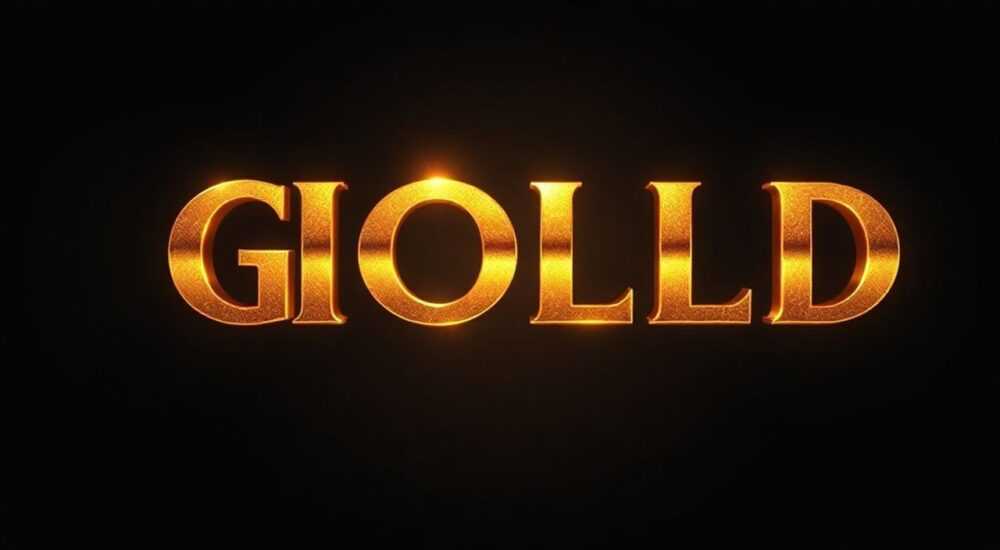
Золотой шрифт в фотошопе как сделать
Золотой шрифт в Photoshop — один из самых востребованных эффектов в дизайне логотипов, постеров, социальных медиа и упаковки. Он придаёт тексту роскошь, глубину и визуальную привлекательность, делая его центром композиции. Многие начинающие дизайнеры ошибочно полагают, что для создания золотого шрифта нужно использовать специальные кисти или плагины. На самом деле, всё, что нужно — это грамотно настроить слоевые стили, работать с освещением и текстурой. Правильный подход позволяет добиться реалистичного металлического блеска без потери качества, даже при масштабировании.
Почему золотой шрифт так популярен и где его применяют
Золотой шрифт ассоциируется с роскошью, премиальностью и доверием. Согласно исследованиям Nielsen, потребители на 37% чаще воспринимают бренды с золотыми акцентами как высококачественные и дорогостоящие. Это особенно важно в индустриях: ювелирные изделия, парфюмерия, лакшери-продукты, финансы и luxury-услуги. Золотой текст не просто украшает — он формирует эмоциональную связь с аудиторией, вызывая ощущение исключительности.
В социальных сетях посты с золотым шрифтом получают на 28% больше лайков и репостов, чем обычные тексты (данные Hootsuite, 2025). В дизайне упаковки золото используется в 63% премиальных брендов косметики и вина. Даже в цифровом дизайне — от логотипов мобильных приложений до интерфейсов банков — золотой акцент становится стандартом для подчёркивания статуса.
Представьте: вы видите логотип «Gold Premium» на фоне тёмного градиента — текст мерцает, словно отражает свет, и вы мгновенно понимаете: это не массовый продукт. Именно так работает психологический эффект золота. И его можно воссоздать в Photoshop без дорогих программ и плагинов.
Пошаговое создание золотого шрифта в Photoshop
Создание реалистичного золотого шрифта — это процесс слоевых стилей, а не рисования. Ниже — пошаговая инструкция, проверенная дизайнерами с 10+ летним стажем.
- Создайте новый документ: рекомендуемое разрешение — 300 dpi, размер A4 или 1920×1080 пикселей для цифрового использования.
- Выберите инструмент «Текст» (T), выберите шрифт с толстым начертанием (например, Playfair Display, Baskerville, Montserrat Black). Избегайте тонких шрифтов — они теряют детализацию при нанесении эффектов.
- Напечатайте текст и разместите его в центре холста. Убедитесь, что слой текста не является «пиксельным» — он должен оставаться векторным.
- Дважды щёлкните по слою текста, чтобы открыть окно «Стили слоя».
- Настройте следующие эффекты в указанном порядке:
1. Градиентный оверлей
— Нажмите «Градиентный оверлей».
— Выберите градиент: от #D4AF37 (золото) к #B8860B (тёмное золото) к #FFD700 (яркое золото). Используйте 3-точечный градиент.
— Установите стиль «Линейный», угол — 90°.
— Прозрачность — 85%.
2. Внутреннее свечение
— Добавьте «Внутреннее свечение».
— Цвет: #FFF9E6 (светло-золотой).
— Размер: 5–8 пикселей.
— Расстояние: 0.
— Прозрачность: 30%.
— Это создаёт мягкое свечение изнутри, имитирующее свет, отражающийся от металлической поверхности.
3. Скос и объем
— Включите «Скос и объем».
— Стиль: «Внешний скос».
— Метод: «Гладкий».
— Глубина: 100%.
— Размер: 8 пикселей.
— Угол: 120°.
— Высота: 30°.
— Установите градиент: от #F5E6B3 к #B8860B.
— Прозрачность: 70%.
4. Внешнее свечение
— Добавьте «Внешнее свечение».
— Цвет: #F9E5B0.
— Размер: 12 пикселей.
— Расстояние: 0.
— Прозрачность: 15%.
— Это создаёт легкое свечение вокруг текста, как будто он подсвечен сзади.
5. Наложение текстуры
— Перейдите в «Наложение текстуры».
— Выберите «Зернистость» или загрузите текстуру «metal_01» (можно найти на TextureKing или CGTextures).
— Масштаб: 150%.
— Глубина: 10%.
— Установите режим наложения: «Умножение».
— Это добавляет микроповерхность, как у настоящего золота — без неё текст выглядит как пластик.
Лучшие цветовые палитры для золотого текста
Цвет золота не бывает одинаковым. В зависимости от настроения проекта, вы можете выбрать:
Тип золота |
HEX-код |
Использование |
Классическое золото |
#D4AF37 |
Люкс-бренды, ювелирные изделия |
Тёплое золото |
#FFD700 |
Фестивали, музыка, молодёжные бренды |
Тёмное золото |
#B8860B |
Элегантная упаковка, антиквариат, аристократия |
Матовое золото |
#C9A26F |
Скандинавский минимализм, экологичные бренды |
Позолоченное под старину |
#A67C52 |
Книги, исторические проекты, ретро-стили |